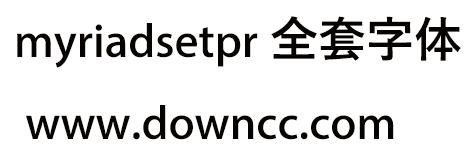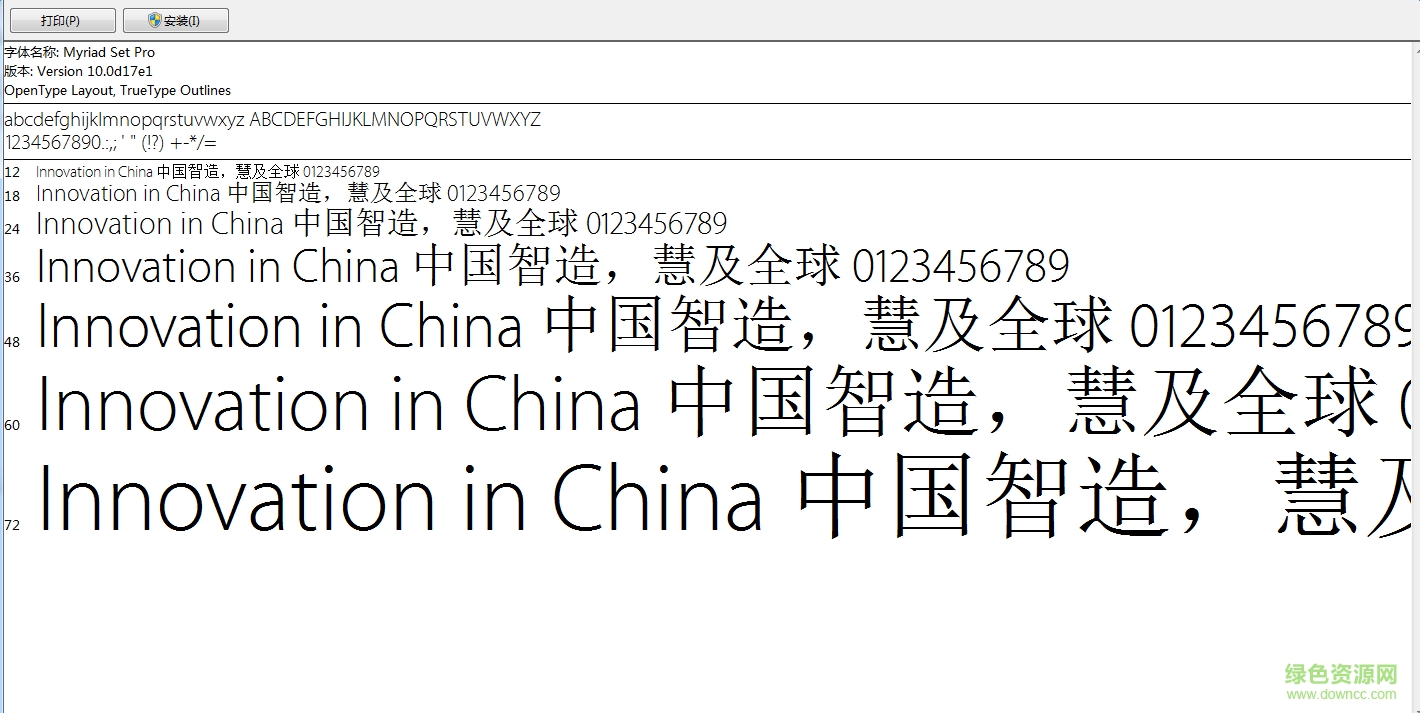
myriad set pro字體是一款ttf格式的英文無(wú)襯線字體,線條勾勒清楚,字體間距均衡,氣質(zhì)出眾,適用的領(lǐng)域十分廣泛,歡迎前來(lái)綠色資源網(wǎng)下載!
myriad set pro字體為蘋果官方字體,筆畫(huà)簡(jiǎn)潔明快,流暢灑脫,不論用在什么方面都不會(huì)顯得出格,需要的小伙伴快來(lái)下載吧!